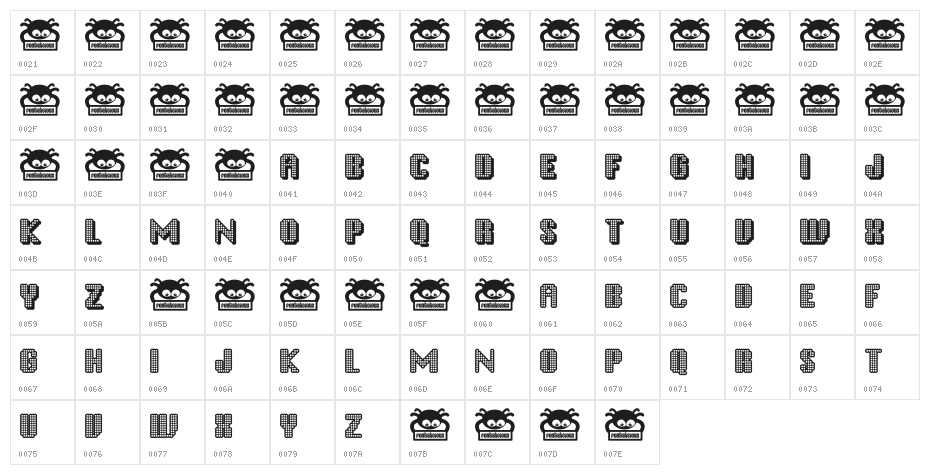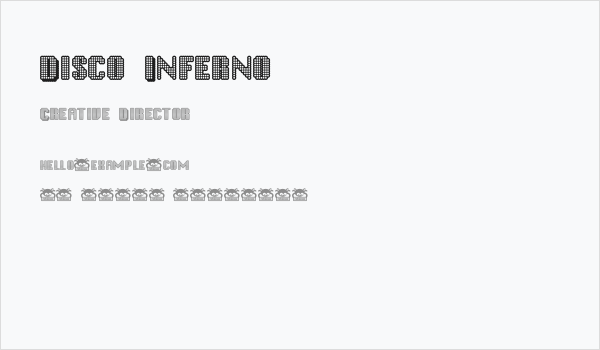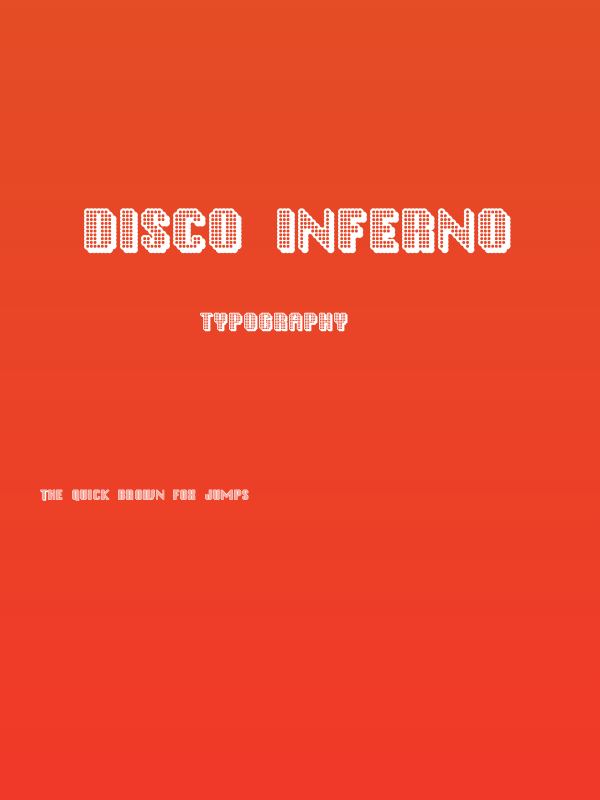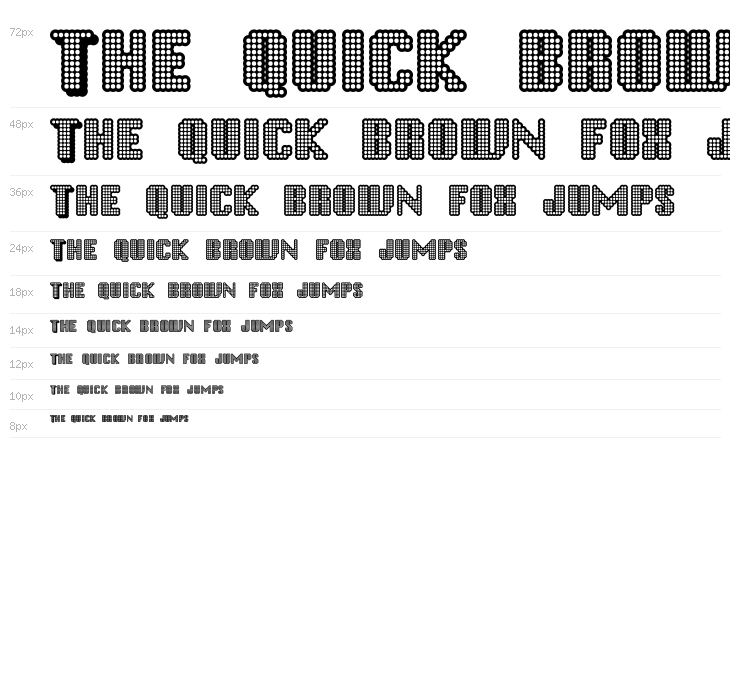
Disco Inferno Font
✎ Dotted
| Gesamtstil | Retro, Decorative |
| Vorgeschlagene Projekte | Ideal for party invitations, event posters, music album covers, and retro-themed designs. |